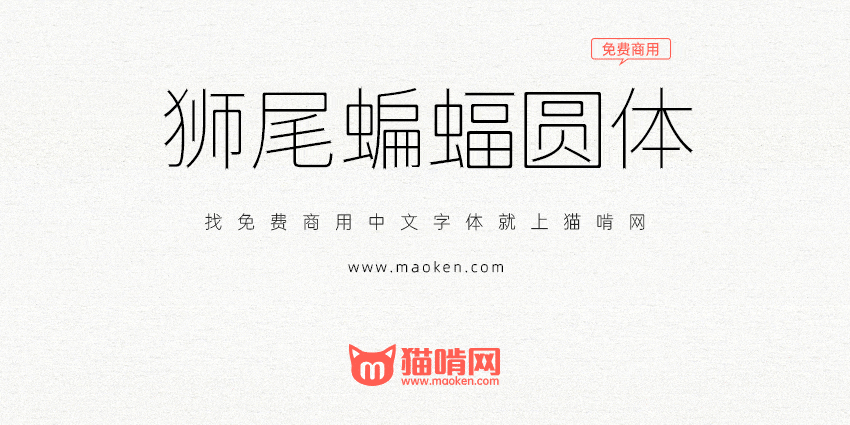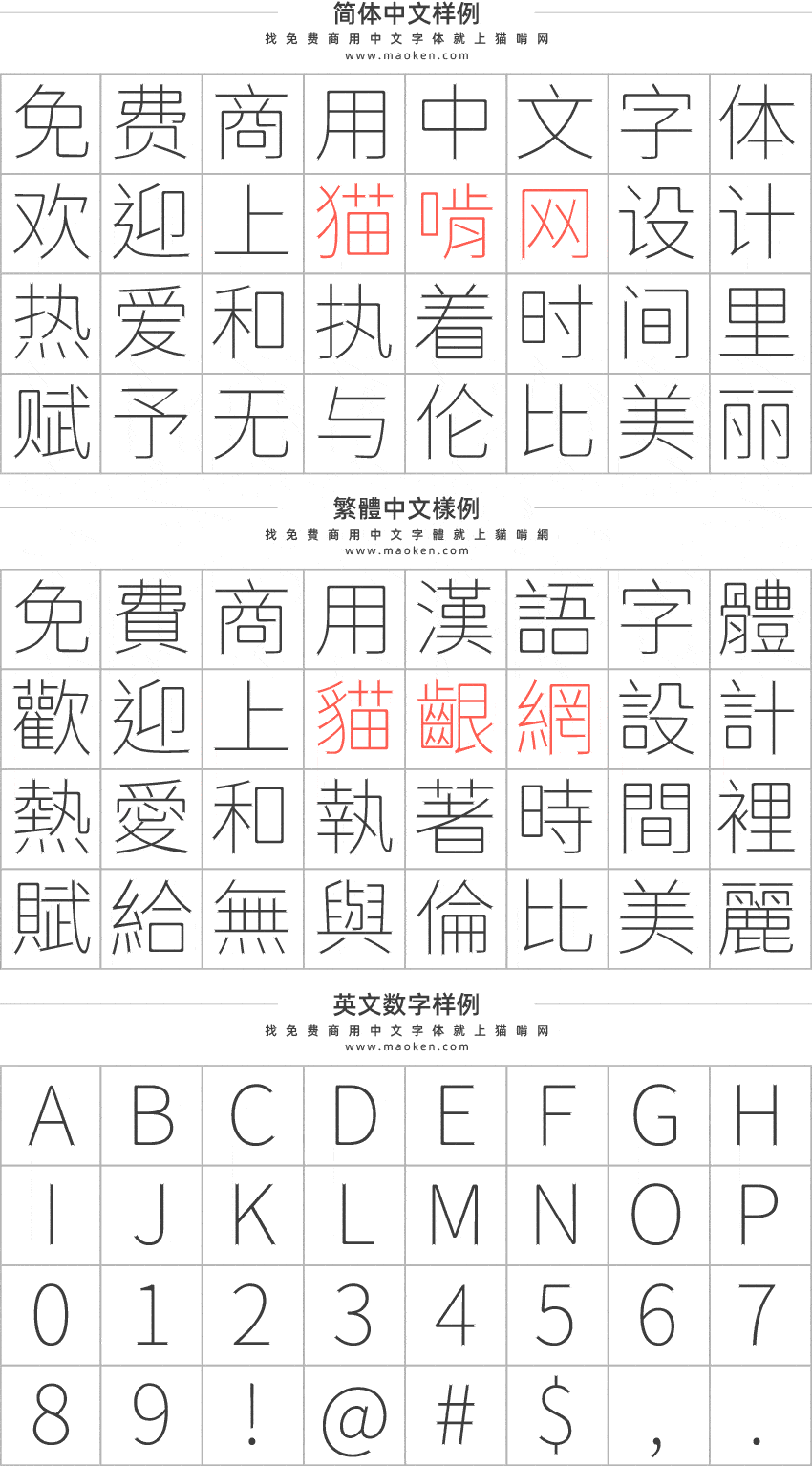
狮尾蝙蝠圆体基于思源黑体笔触长耳朵和拔脚改造,更加简明现代化的字体。支援简体中文、繁体中文、韩文与日文;欢迎大家自由应用、自由优化、自由改作!
狮尾三角黑体的特色是,「一」字的开头和结尾笔触由平头换成蝙蝠耳朵形状。
Ver 2.099(2020/09/05)
- 让「蝙」字的户部件套用到长耳朵的效果。原本的 ver 2.095版这一个部件没套用到效果。
Ver 2.095(2020/09/04)
- 狮尾蝙蝠圆体第一版正式发布